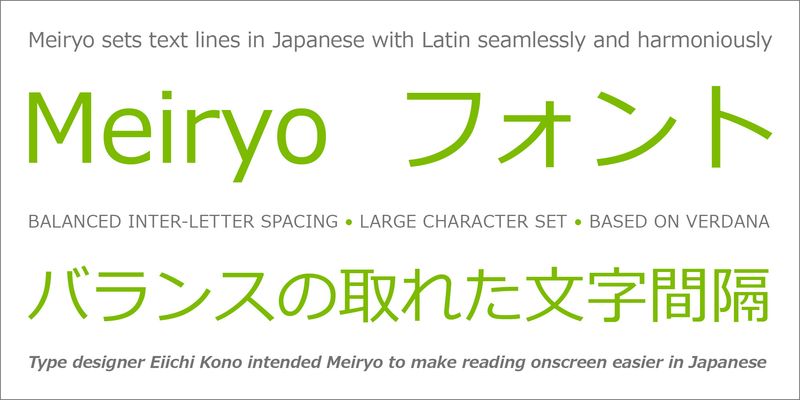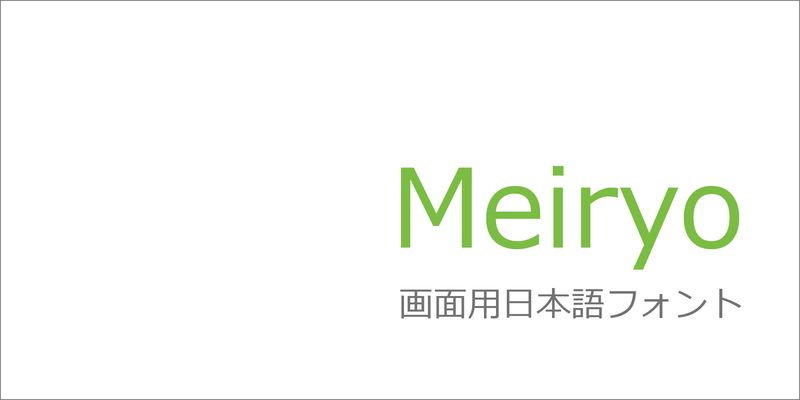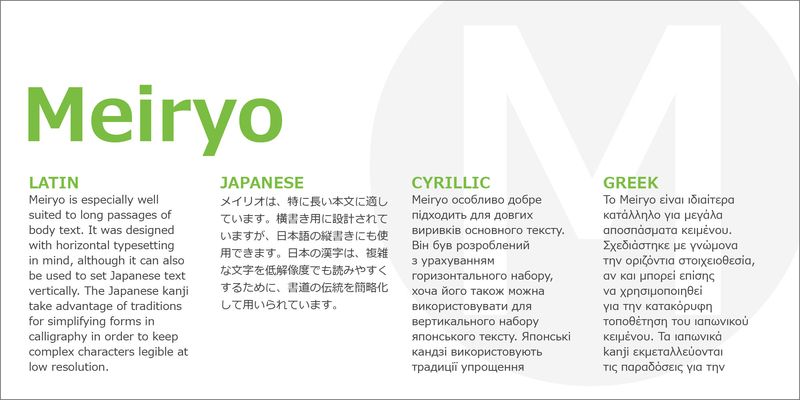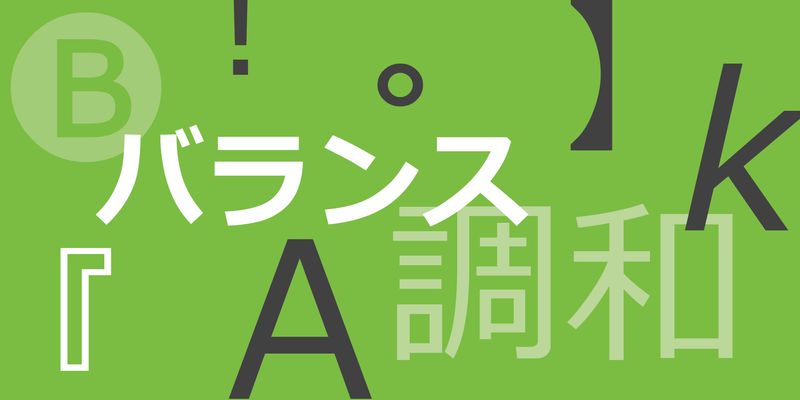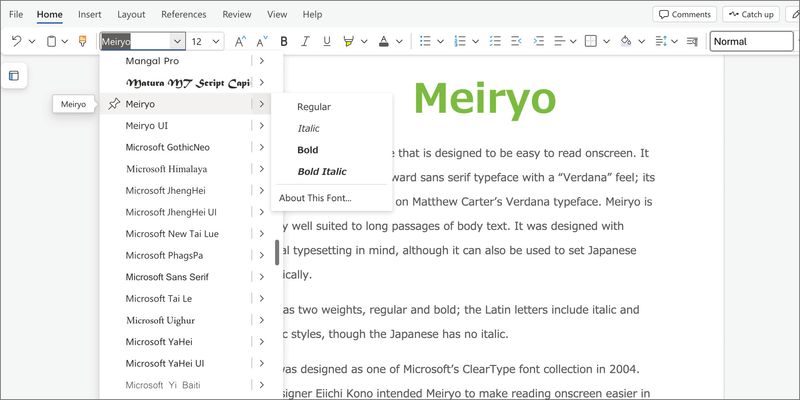
„Meiryo“ ist eine japanische Schrift, bei der die Lesbarkeit am Bildschirm im Vordergrund steht. Die Schrift ist klar, einfach und schnörkellos und erinnert an die „Verdana“. Tatsächlich basieren die lateinischen Buchstaben auf der Verdana von Matthew Carter. Die Meiryo eignet sich besonders für lange Fließtexte. Die Schrift wurde für die horizontale Schreibrichtung (横書き (yokogaki)) entwickelt, kann aber auch für die vertikale Schreibrichtung (縦書き, tategaki) japanischer Texte verwendet werden.
Die Meiryo ist in zwei Schriftstärken erhältlich: Regular und Bold. Für die lateinischen Buchstaben gibt es zusätzlich Italic und Bold Italic, während für das japanische Schriftsystem keine Kursivschrift vorgesehen ist.
Die Meiryo entstand 2004 als Teil der Microsoft ClearType-Schriftkollektion. Ziel des Schriftdesigners Eiichi Kono war eine gute Lesbarkeit am Bildschirm. Die japanischen Kanji-Schriftzeichen nutzen die traditionelle Vereinfachung der Formen in der Kalligrafie, um die Lesbarkeit komplexer Zeichen bei geringer Auflösung zu wahren. Die lateinischen, griechischen und kyrillischen Buchstaben der Meiryo stammen von Matthew Carter und basieren auf seiner Schrift Verdana, die speziell für das Lesen westlicher Sprachen am Bildschirm entwickelt wurde.